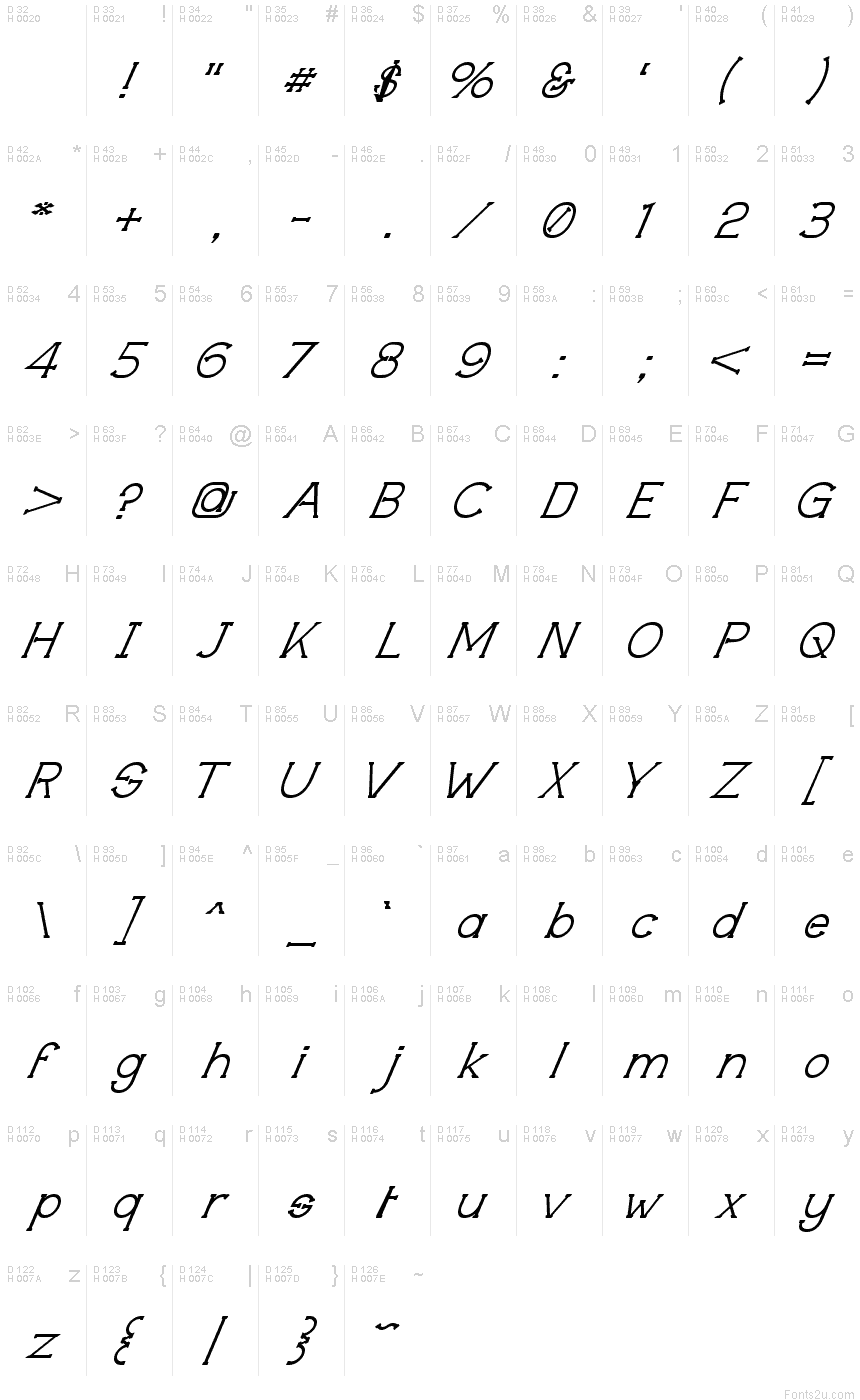
Technically Insane Superitalic
Technically Insane Superitalic, autorstwa GemFonts98, to darmowy krój pisma typu display w stylu techno o ostrym, dynamicznym rytmie i wyraźnie futurystycznym nachyleniu. Litery sprawiają wrażenie smukłych i szybkich, łącząc cienkie kreski, ostre łączenia i cięte krzywizny, co nadaje fontowi niespokojną, niemal mechaniczną energię, przy jednoczesnym zachowaniu eleganckiego, nowoczesnego charakteru.
Krój naturalnie pasuje do plakatów sci-fi, logotypów gier, ulotek klubowych, nagłówków i okładek, gdzie darmowy font ma przekazywać ruch, a nie masę. Wykorzystaj go do krótkich nazw, brandingu technologicznego, grafik inspirowanych interfejsami czy szybkich tytułów – agresywny kąt pochylenia i przypominające igły detale wykonują większość pracy.